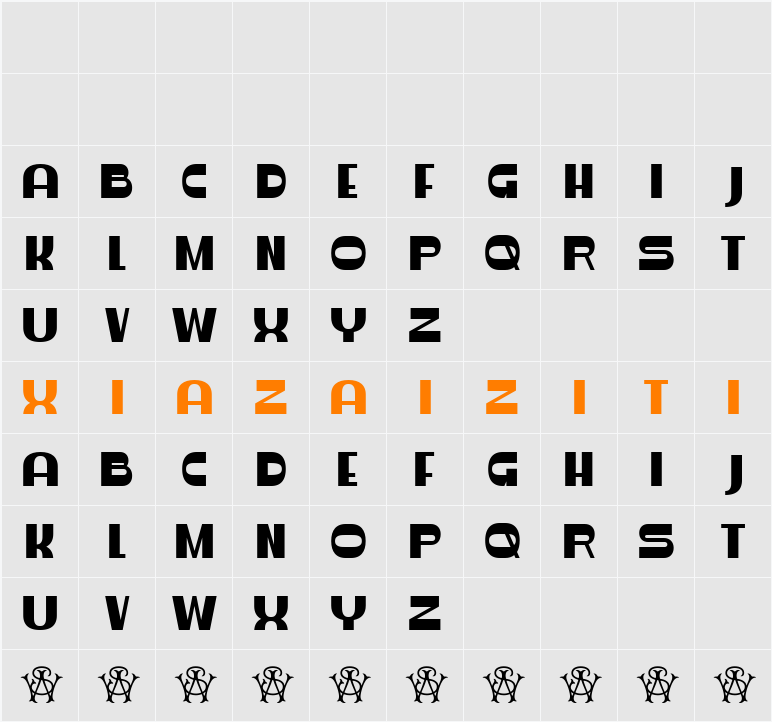
ws Pontac Demo
ws Pontac Demo,这款字体结构工整、笔画清晰,兼顾美观与易读性,适用于标题、正文、海报、包装、LOGO 等多种场景。字形优雅稳定,风格百搭耐看,适配日常排版与创意设计,让文字呈现更舒适、更具质感。ws Pontac Demo一笔一画,皆是细节,以均衡的比例、流畅的线条打造舒适视觉体验,字形端正大气,风格简约现代。无论是商业设计、品牌宣传还是日常排版,都能轻松驾驭,让文字更有格调与力量。ws Pontac Demo字体下载。
• 设计师: Miftahul Habib